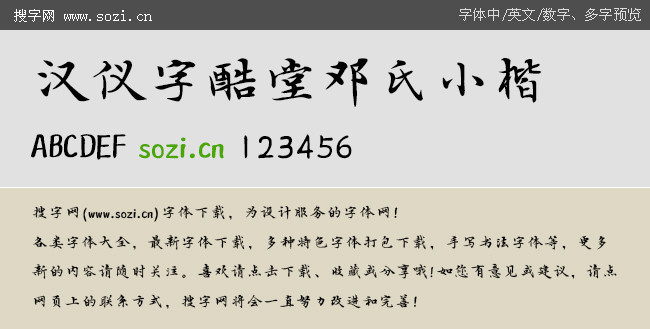
漢儀字酷堂鄧氏小楷
搜字網(wǎng)給大家提供一款漢儀字酷堂鄧氏小楷中文字體下載,漢儀字酷堂鄧氏小楷字體是一款名人抄本復刻體,字體來源于鄧散木《篆刻學》,字體飽滿生動,筆畫矯健活潑,適合應用于藝術設計、平面宣傳設計、網(wǎng)頁設計、包裝設計等場合使用。(本字體為個人非商用版,如需要商用請聯(lián)系漢儀公司購買版權)